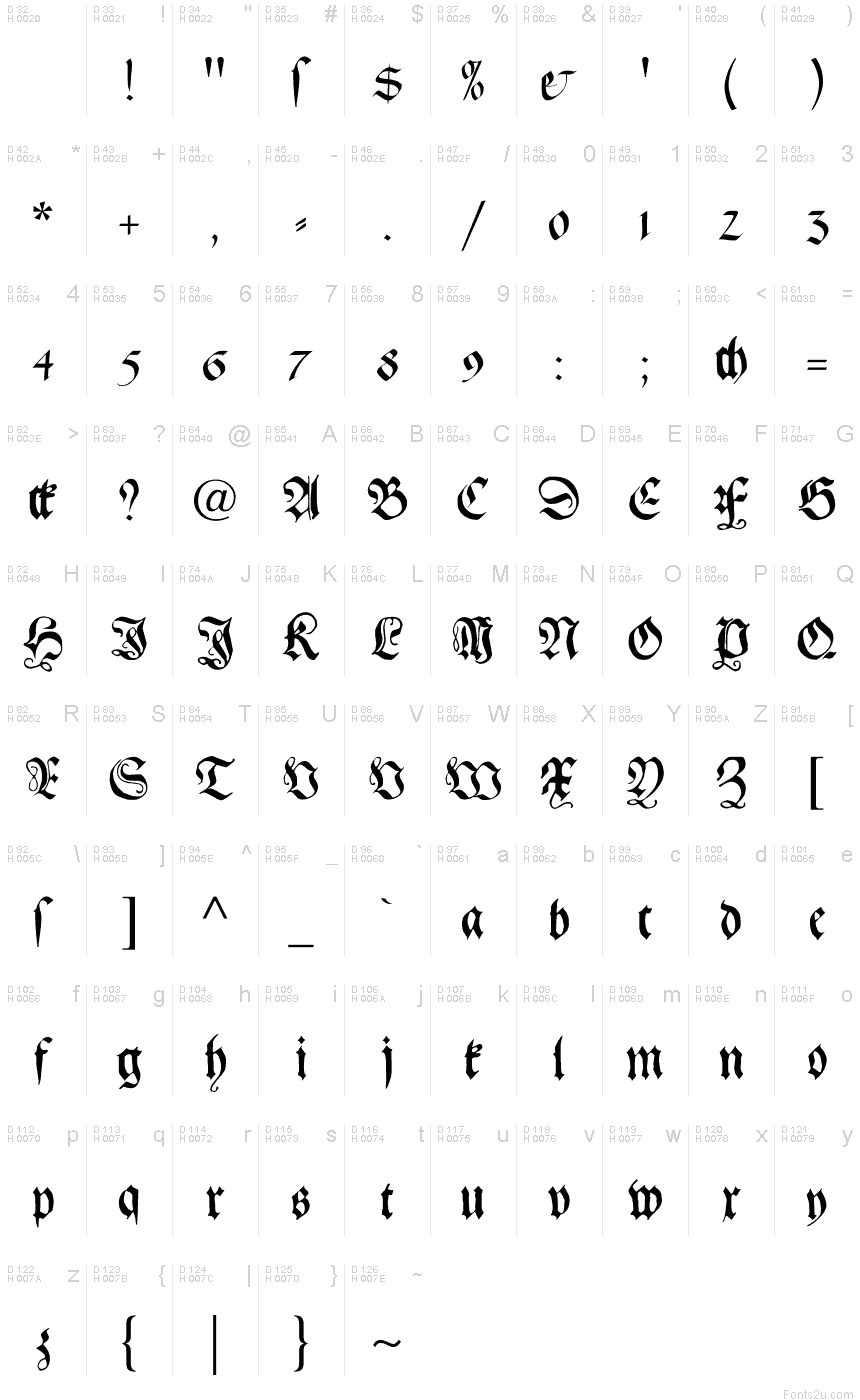
Gebetbuch Fraktur
Gebetbuch Fraktur od Typographer Mediengestaltung to darmowy, gotycki krój pisma, który sprawia wrażenie, jakby został wyjęty prosto ze starego modlitewnika. Ciężkie, atramentowe pociągnięcia, ciasne łuki i ostre, niemal kolczaste szeryfy nadają każdemu słowu ciężar napisu rytego w kamieniu lub kaligrafowanego szeroką stalówką. Rytm pisma jest gęsty i dramatyczny, dzięki czemu każda linijka niesie ze sobą atmosferę ceremonii i dawnych czasów.
Ten darmowy font doskonale sprawdza się na okładkach książek fantasy, plakatach historycznych, logotypach zespołów, materiałach do gier LARP, grafikach do escape roomów oraz nastrojowych zaproszeniach. Użycie Gebetbuch Fraktur w większym rozmiarze pozwala zachować jej skomplikowaną fakturę, a zestawienie z czystym, nowoczesnym krojem bezszeryfowym zapewnia czytelność i stabilność projektu.